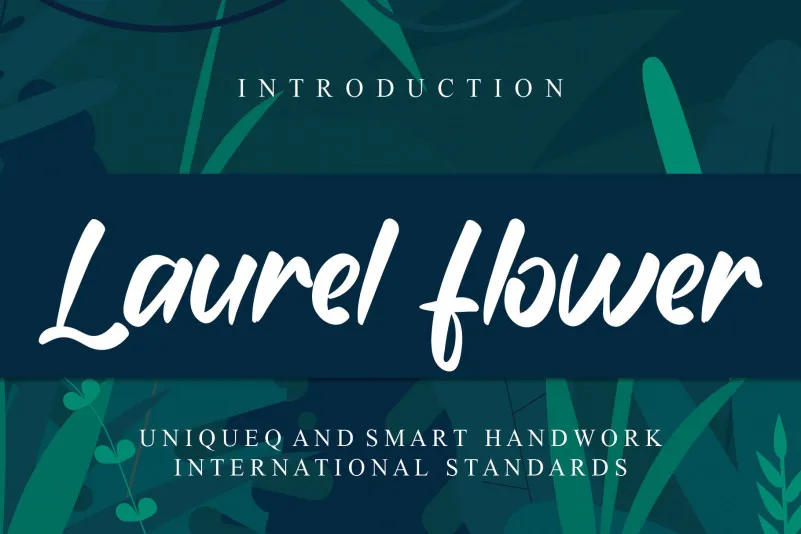
Laurel flower Script Font – Download Grátis
Laurel Flower Script Font é uma elegante fonte de escrita a mão que traz uma mistura única de tendência e sofisticação. Com letras distintas e bem redondas, esta fonte faz do seu uso um verdadeiro ato de arte. Suavemente harmoniosa, ela é perfeita para aqueles que desejam incorporar nuances elegantes em seus designs digitais. Use-la nos mais variados formatos pode revelar a incrível versatilidade deste tipo. Que tal explorar esta fonte e ver como ela molda seu design digital?